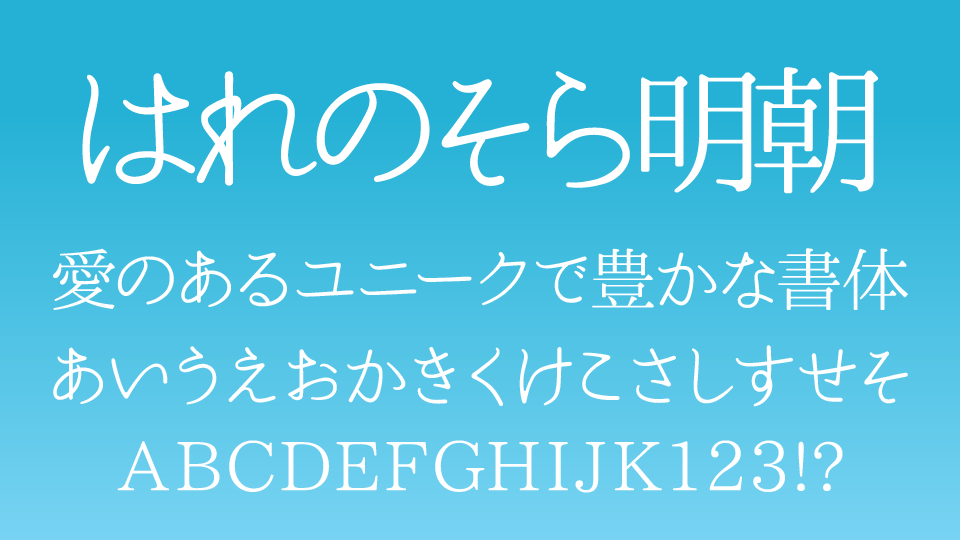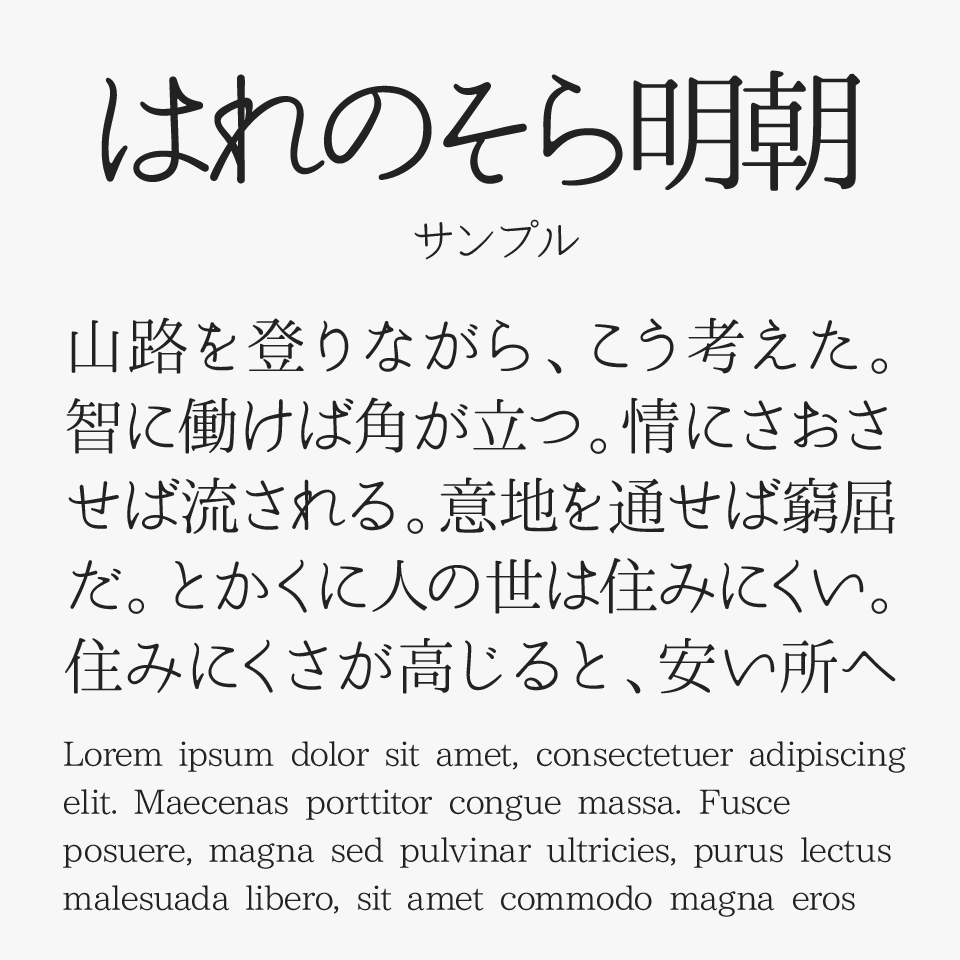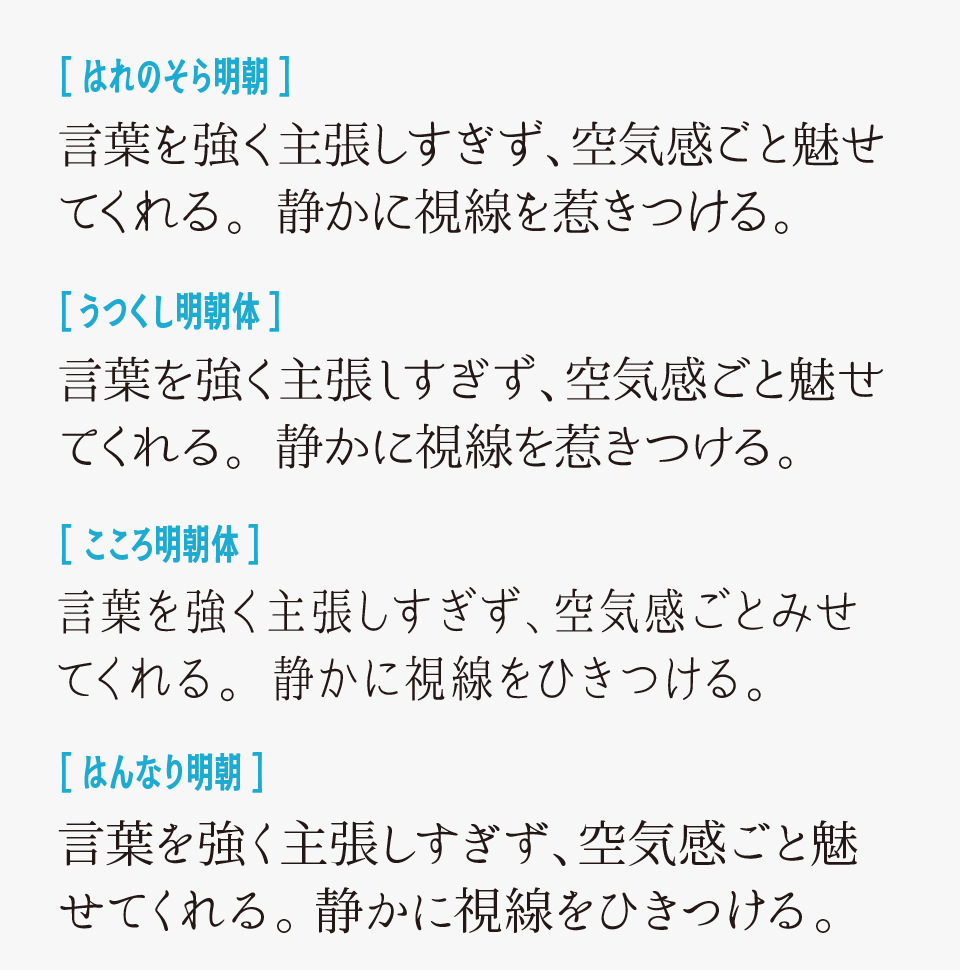
はれのそら明朝
はれのそら明朝フォントは、角丸ですっきりとした印象に仕上げられた明朝体フォントです。
交差部分にはほんのり墨だまりが取り入れられており、オールド系明朝体の要素も感じられるため、「晴れの空」というフォント名にぴったりなやわらかさの中に伝統的な美しさを感じられるデザインとなっています。
美しく整ったはね・はらいも印象的で、上品さや高級感を演出したいデザインと相性の良いフォントです。特に、大人女性向けのデザインやファッション・コスメ・ブライダル系のビジュアルなどにもぴったりです◎
はれのそら明朝を、オールドスタイル系で、すっきりとした雰囲気を持つ明朝体フォントと比較してみると、やわらかく自然な空気感が特に魅力的です。
比較フォントは、「うつくし明朝体」「こころ明朝体」「はんなり明朝」と比較していますが、どのフォントも独特な雰囲気がステキな明朝体ので、あわせてチェックしてみてください。
収録文字は、ひらがな・カタカナの書体で、漢字、記号、英数字などはIPA明朝体で補完されています。